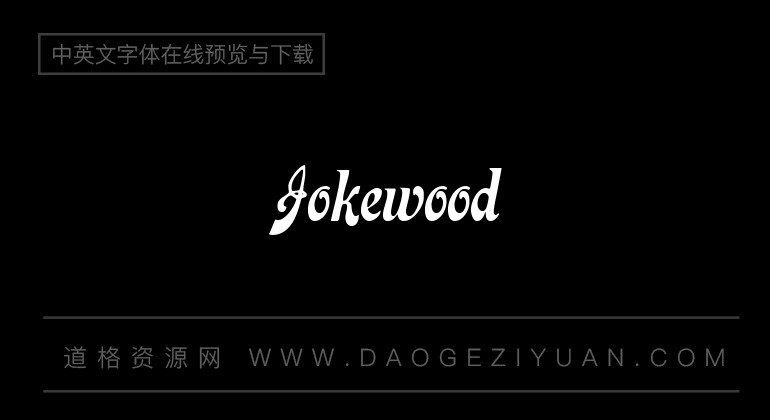
Jokewood
Jokewood 是一款具有轻松、活泼、有趣的手写字体,它具有浓厚的街头和休闲气息,适合用于海报、T恤、商标、标语、漫画、标题等等。它的字母是由曲线和折线组成,有着浓厚的街头气息,充满活力,可以让您的设计更加生动活泼。
Jokewood是一款非常不错的手写艺术字体,具有很好的视觉感,适合于文化类的宣传设计、商业类品牌的广告和产品包装设计以及个性化文字排版等较多场景。